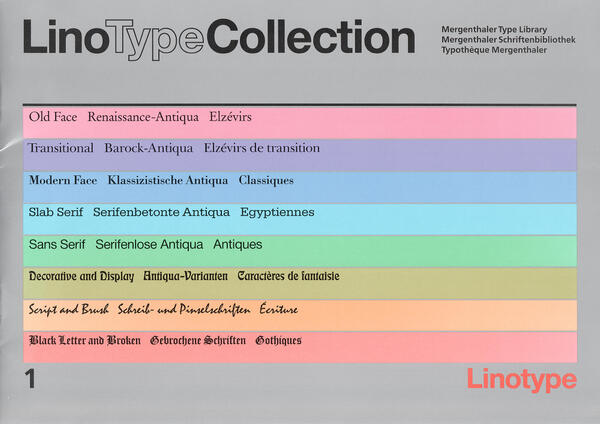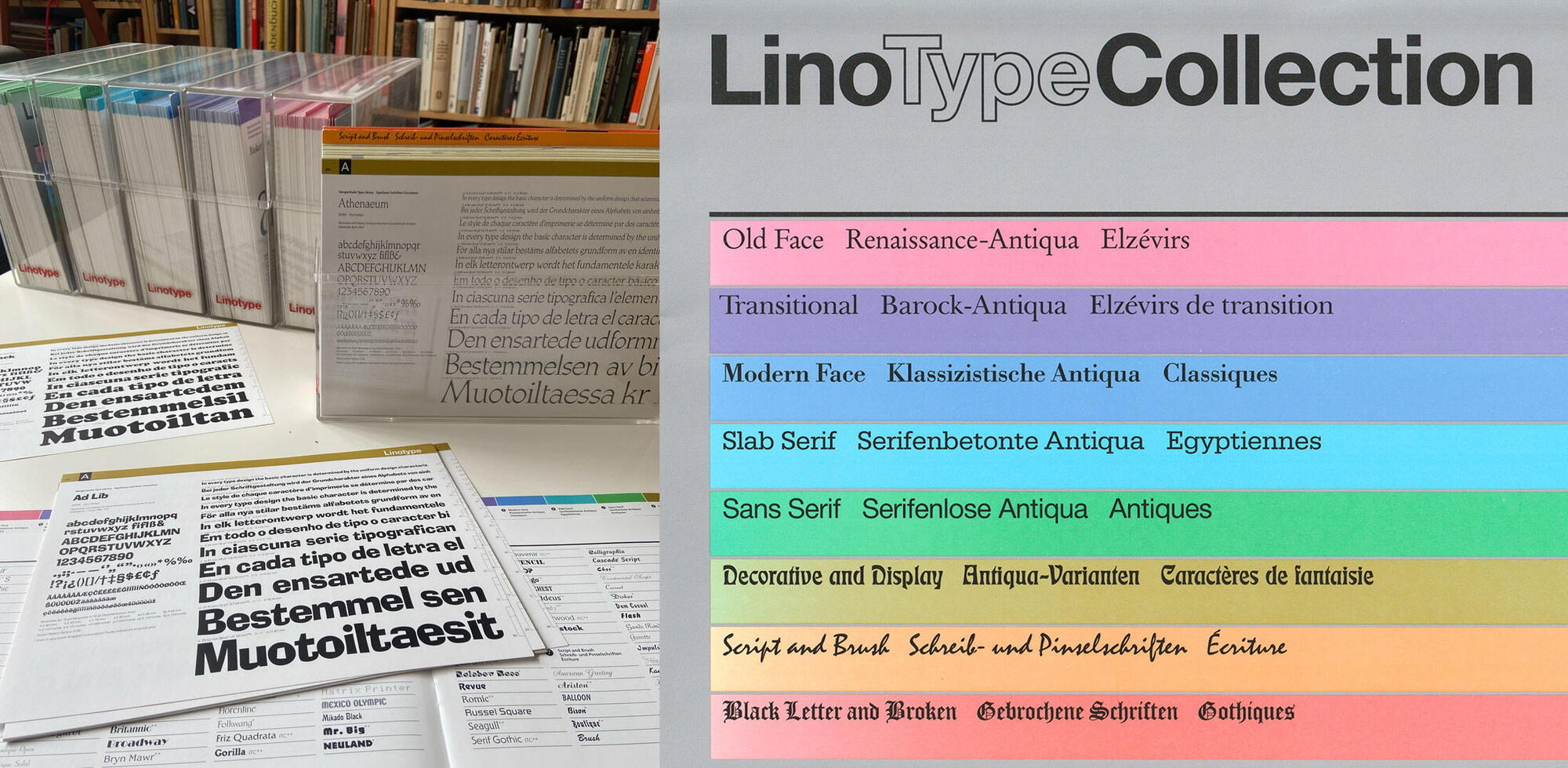
Die Linotype Collection ist eine Schriftmustersammlung der Linotype GmbH aus den 1980er-Jahren. Sie zählt zu den umfangreichsten, jemals produzierten Schriftmustern und war so groß, dass Linotype sogar einen passenden Rollwagen für die Aufbewahrung der Tausenden Einzelblätter in 6 Acrylboxen anbot.
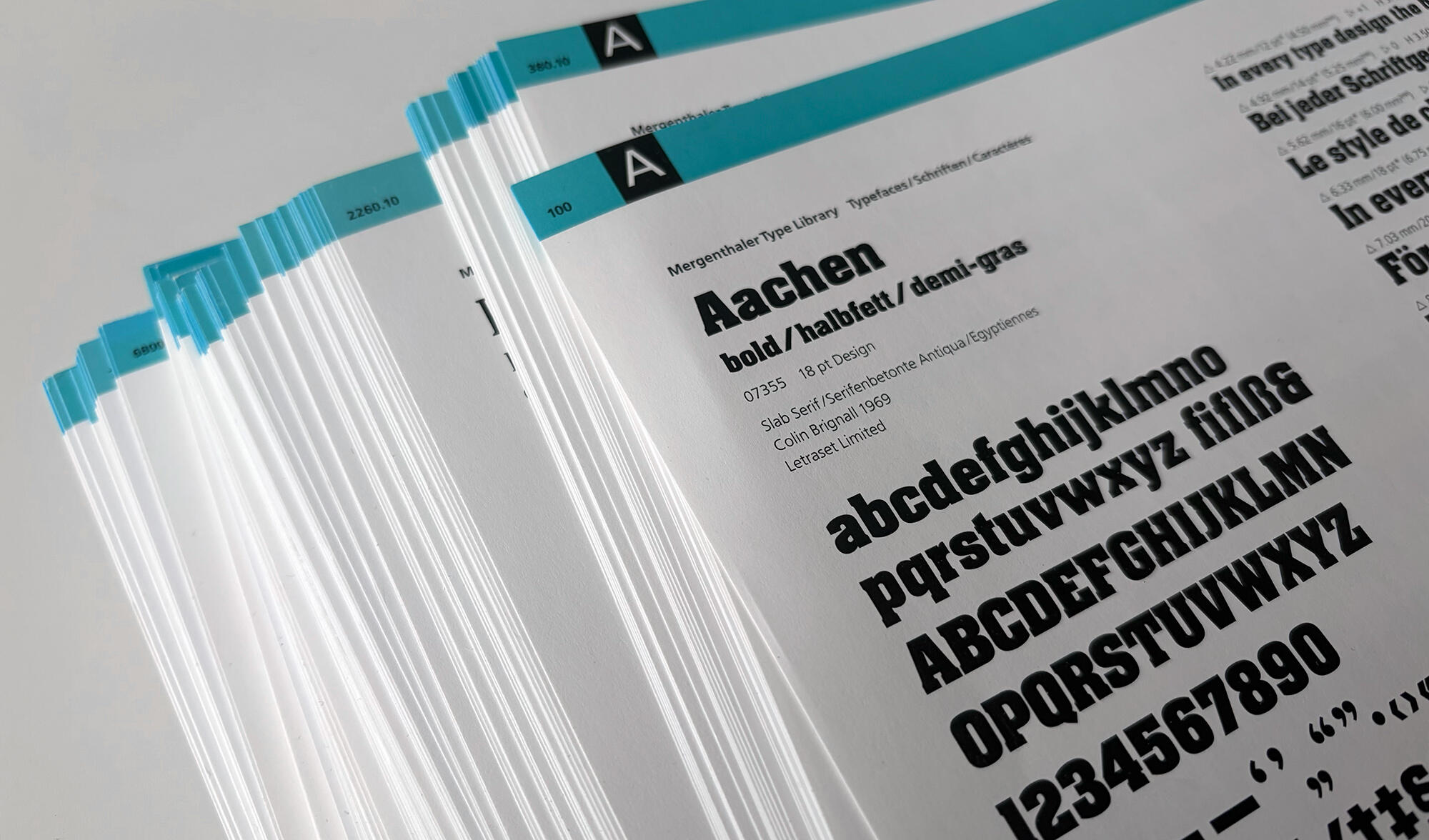
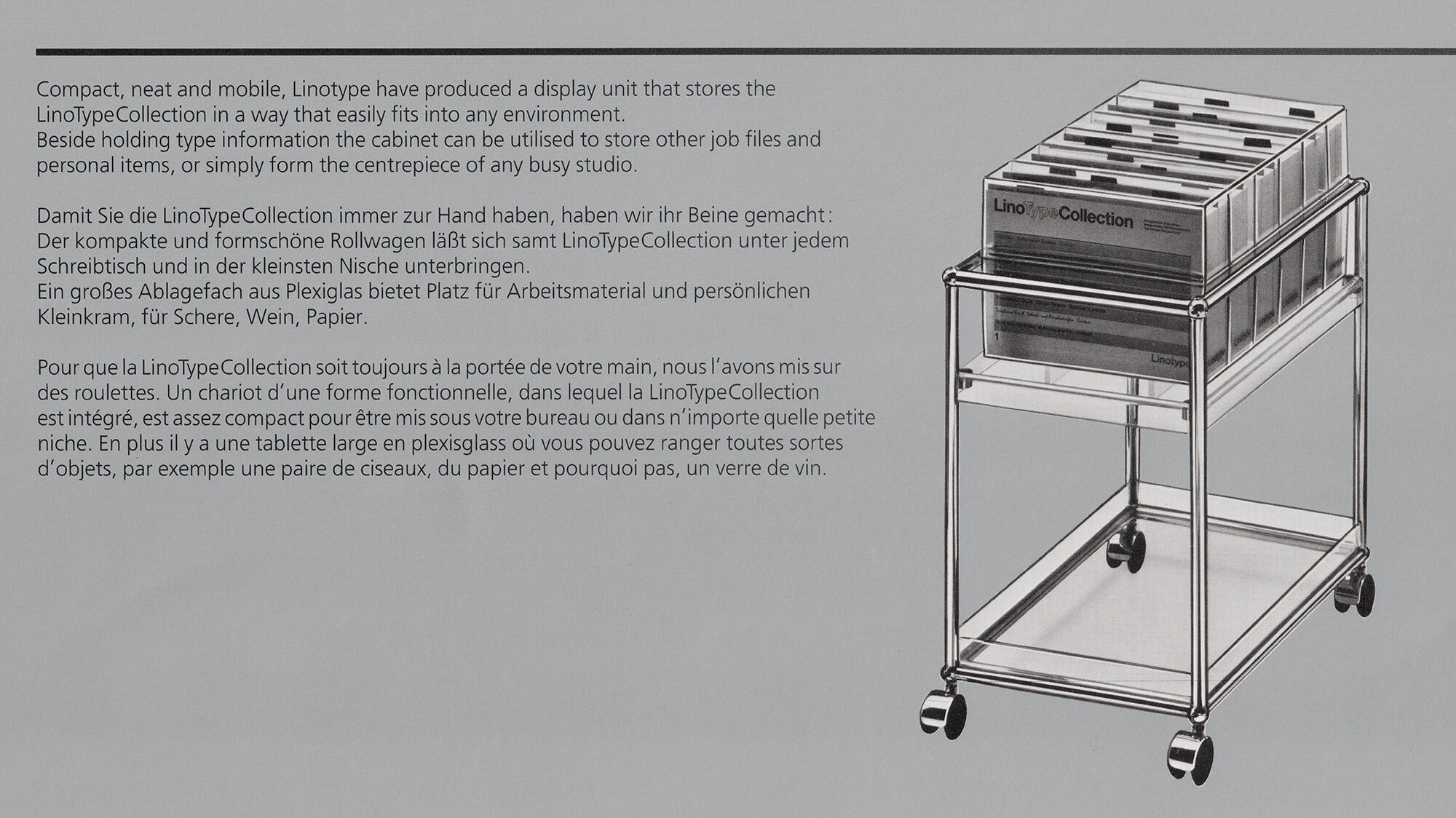
Die Sammlung demonstriert den Stand der Fotosatzschriften in den 1980er-Jahren. Neben Linotype-Schriften werden auch andere, damals von Linotype in Lizenz vertriebene Schriften (etwa von ITC, Monotype, Letraset etc.) gezeigt. Die farbkodierten Muster sind kategorisiert in die Bereiche:
Renaissance-Antiqua
Barock-Antiqua
Klassizistische Antiqua
Serifenbetonte Antiqua
Serifenlose Antiqua
Antiqua-Varianten
Schreib- und Pinselschriften
Gebrochene Schriften
Alle Schriften werden mit komplettem Figurenverzeichnis und Satzbeispielen auf einem herausnehmbaren, beidseitig bedruckten Blatt gezeigt.